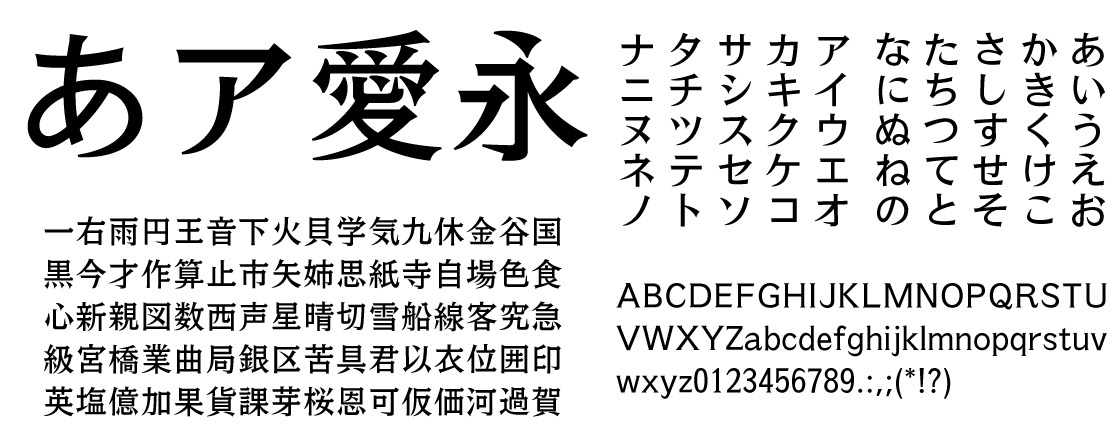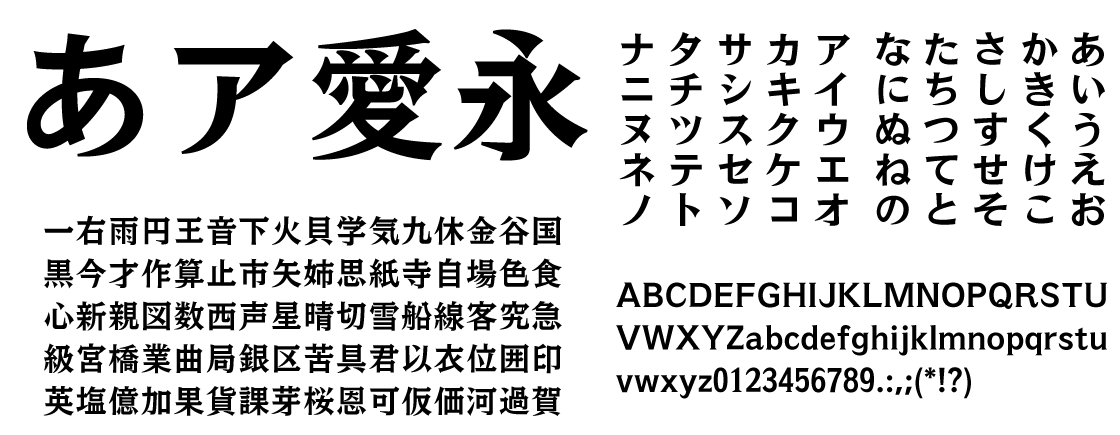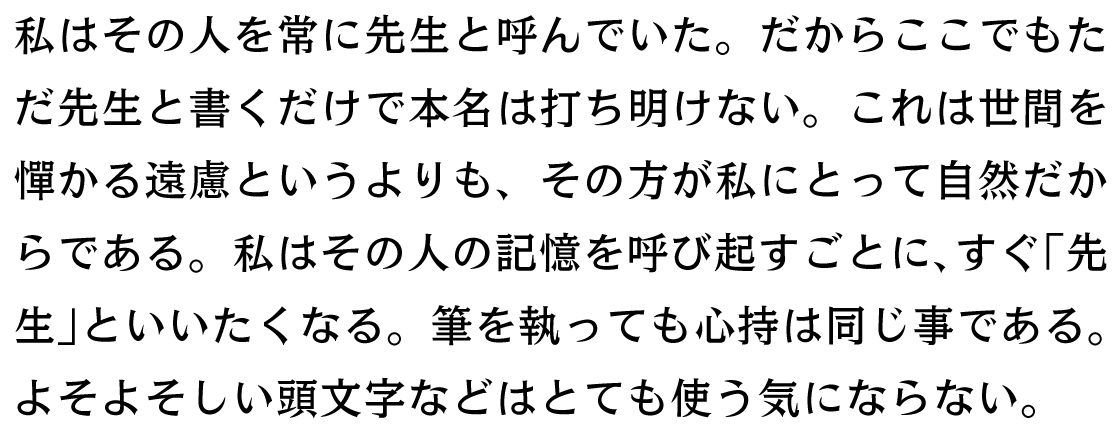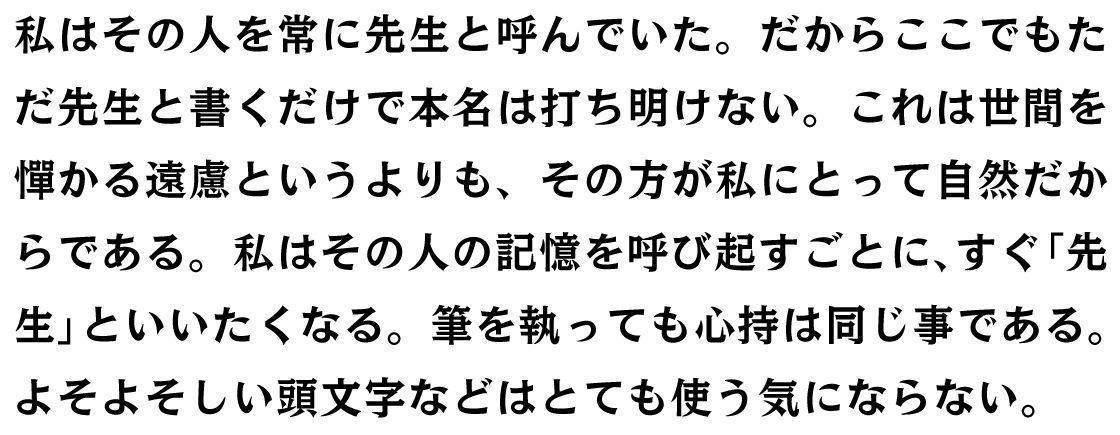
モトヤホンコン
書体解説
モトヤホンコンは、明朝体のようなデザインと、ゴシック体を思わせる力強さを併せ持った書体です。勢いのある文字が特徴的なこの書体は、中国・香港で着想を得たことから「ホンコン」と命名され、1972年に活字書体として販売しました。今回、活字時代の雰囲気はそのままに、デザインをさらに洗練させ、デジタルフォントとして帰って来ました。